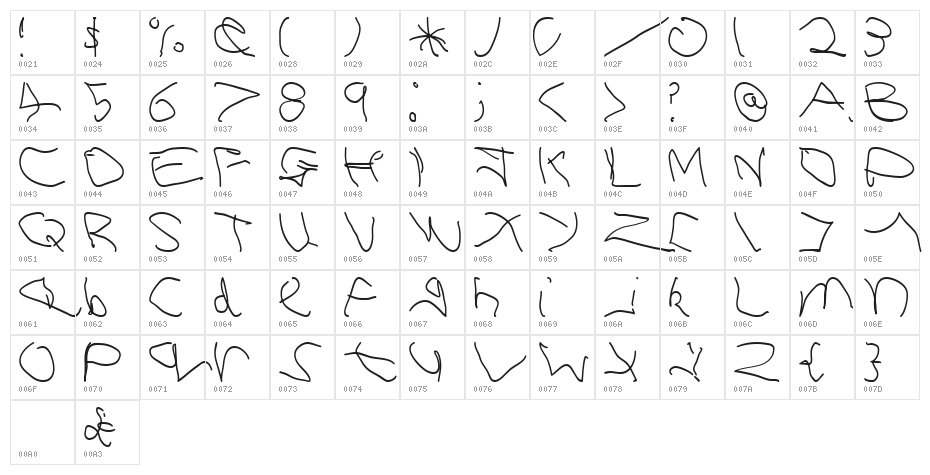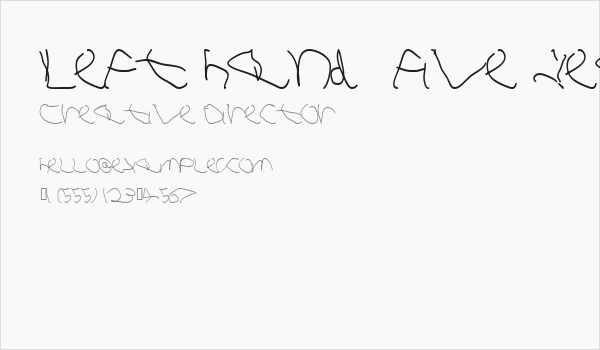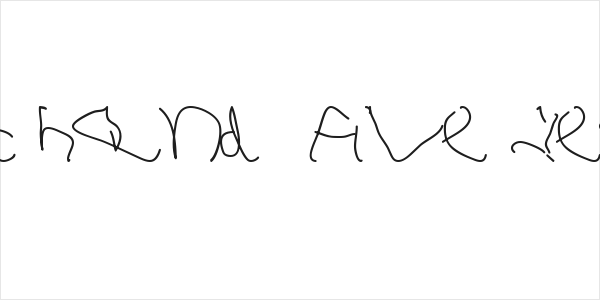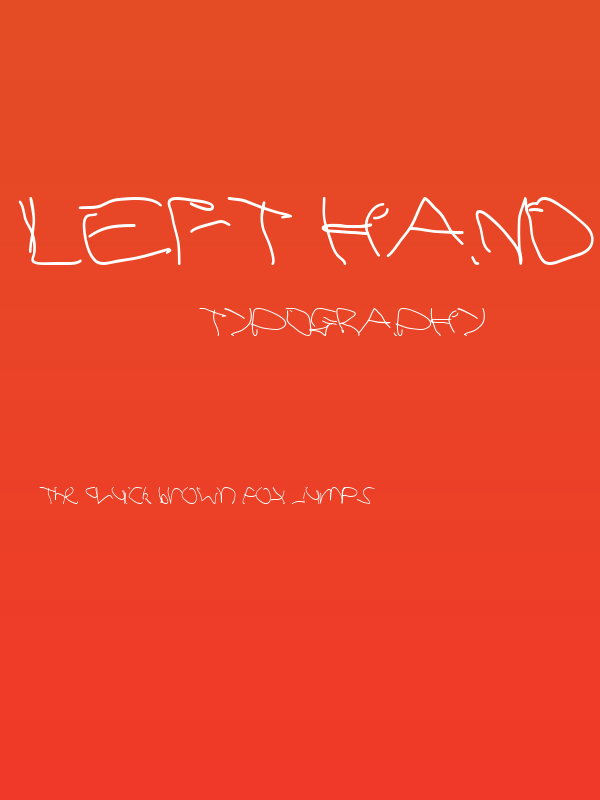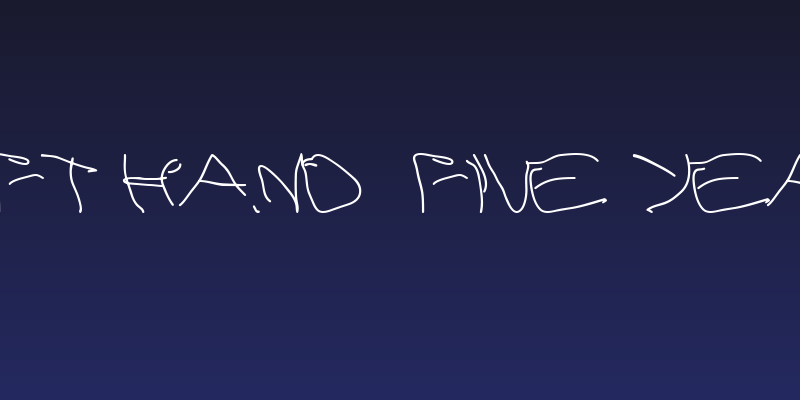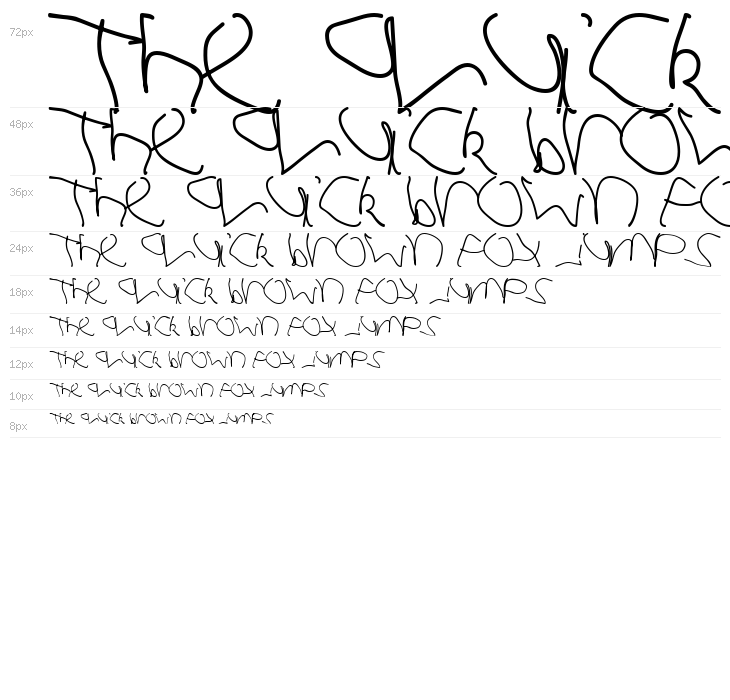
Left hand five years Font
| 用途 | Logos, Headlines, Artistic projects |
| おすすめプロジェクト | Ideal for children's book covers, playful greeting cards, casual invitations, or any project that benefits from a whimsical, personal touch. |